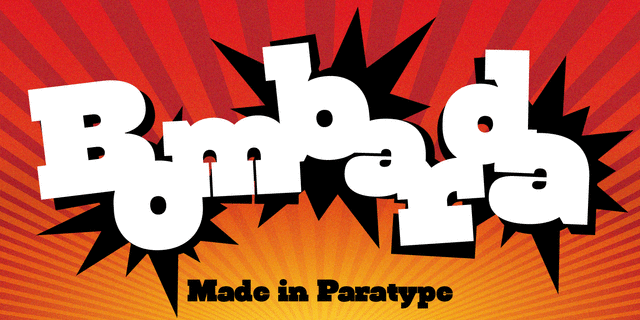
Bombarda — это большая пушка, и конечно, шрифт с таким названием должен иметь особые габариты, чтобы заставить текст звучать громко и мощно. Благодаря экстремальной толщине основных штрихов и максимально возможным засечкам, он будет отлично смотреться на обложках комиксов, красочных заставках компьютерных игр и в любых других применениях, где смыслу заголовков необходимо придать особый вес. Шрифт разработан Александром Любовенко и выпущен компанией Паратайп в 2016 году.